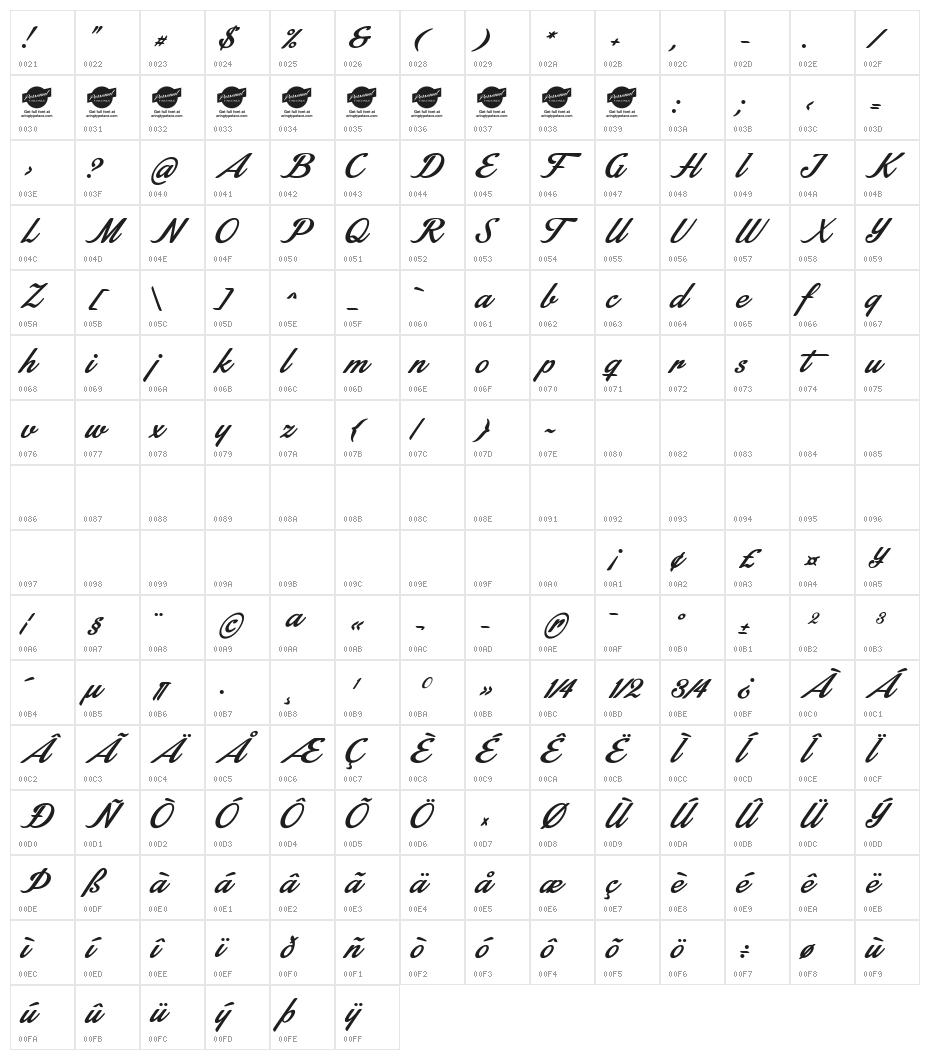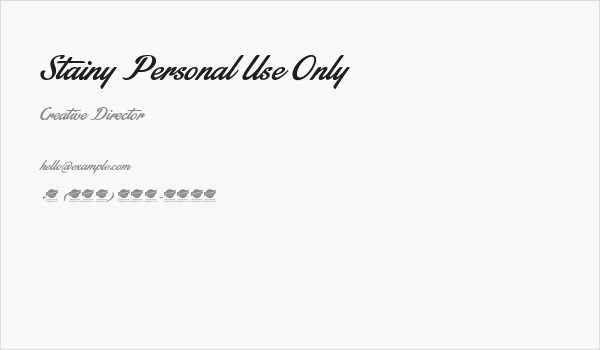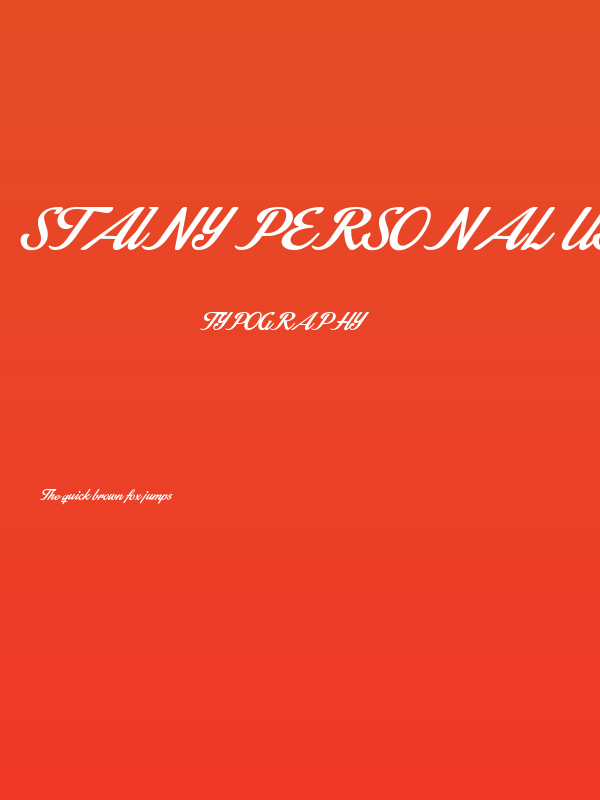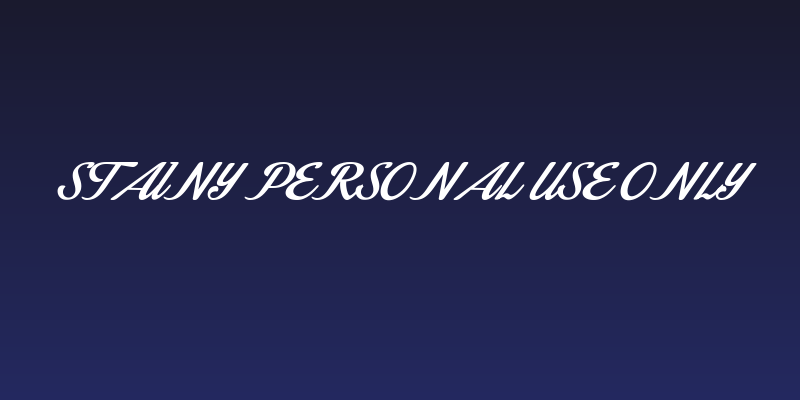
Stainy Personal Use Only Font
| Caso d'uso | Logos, Invitations, Greeting Cards |
| Progetti proposti | Ideal for branding, invitations, greeting cards, and logo design, where a touch of elegance and personality is desired. |